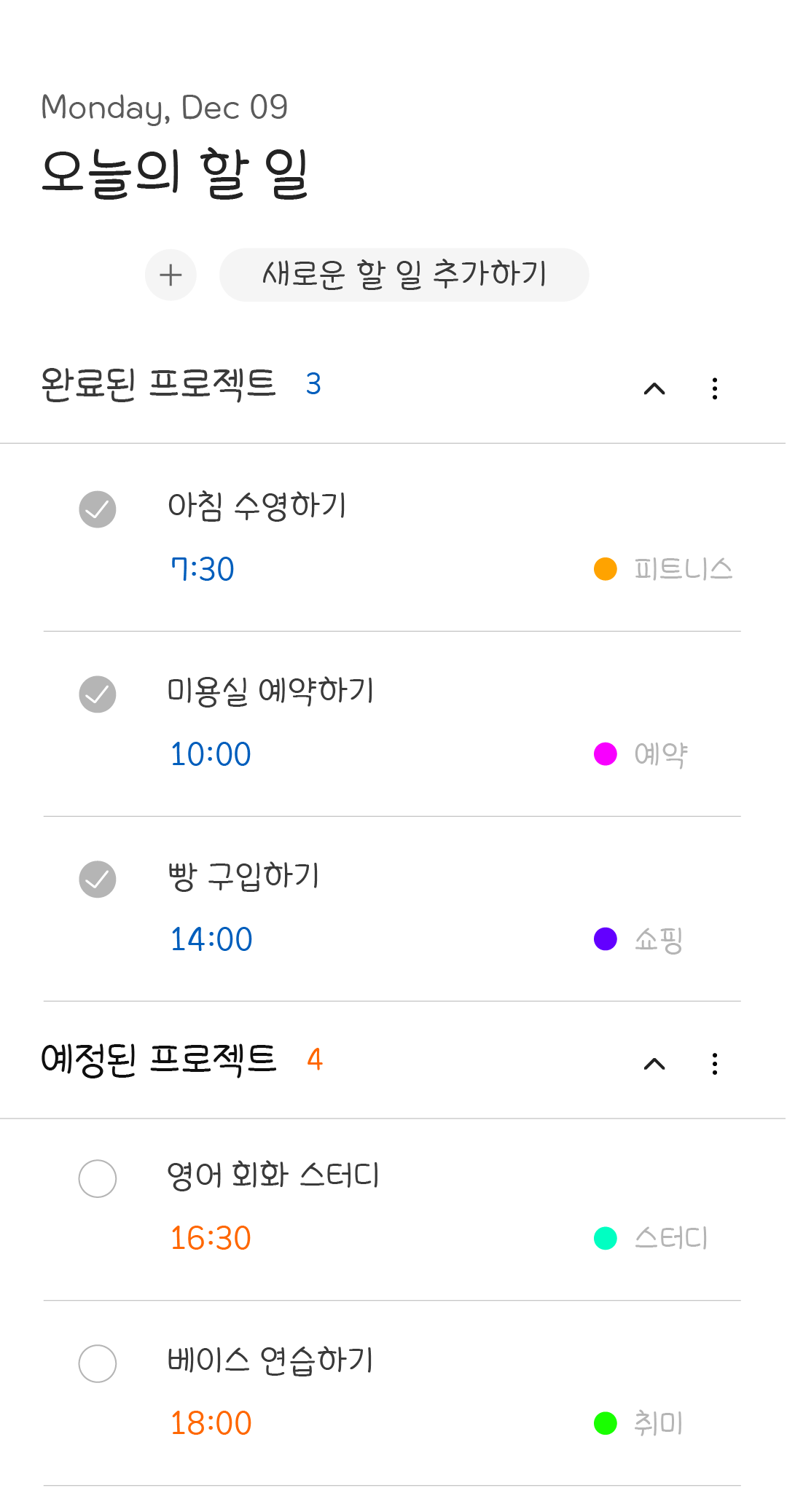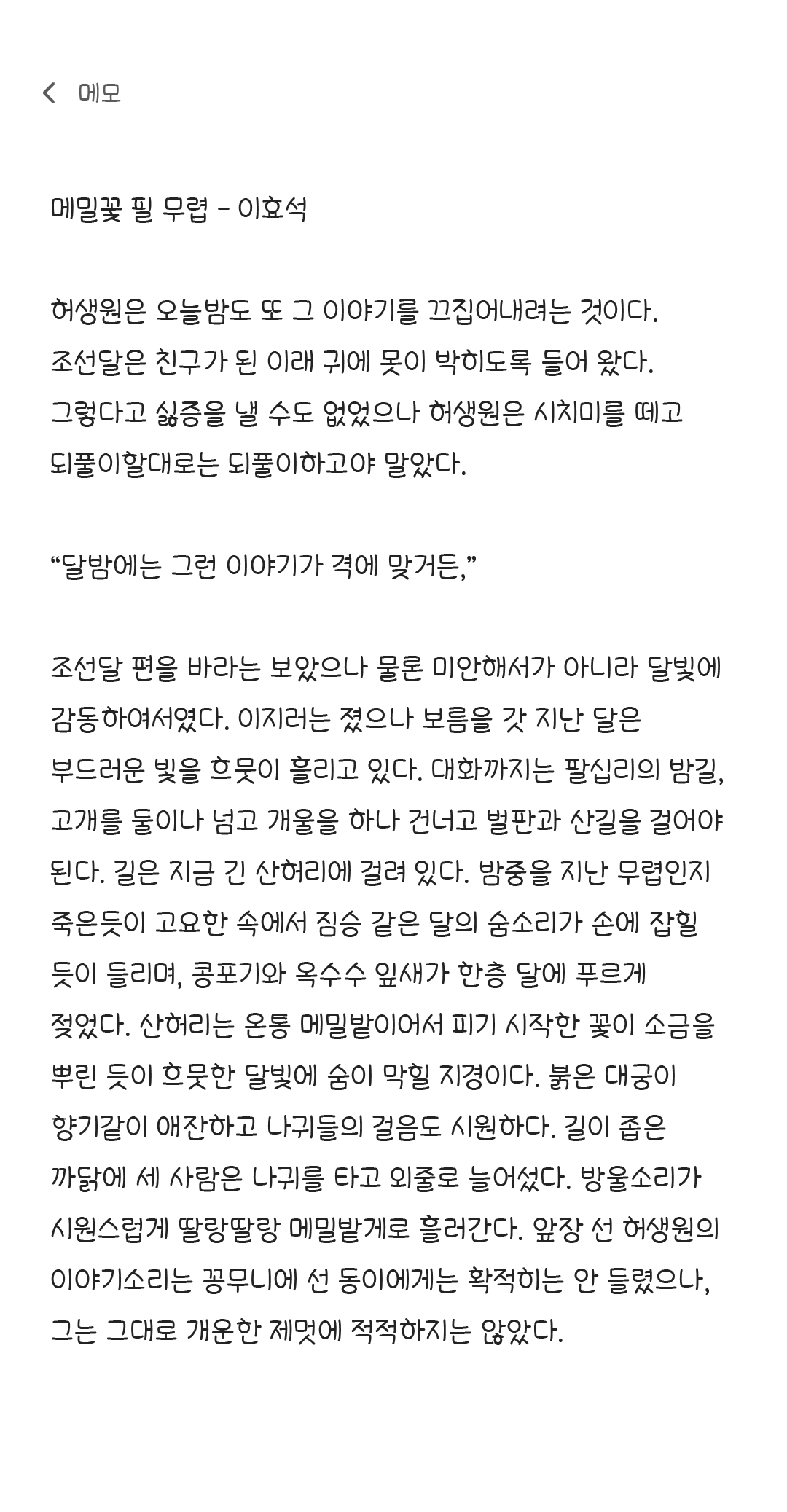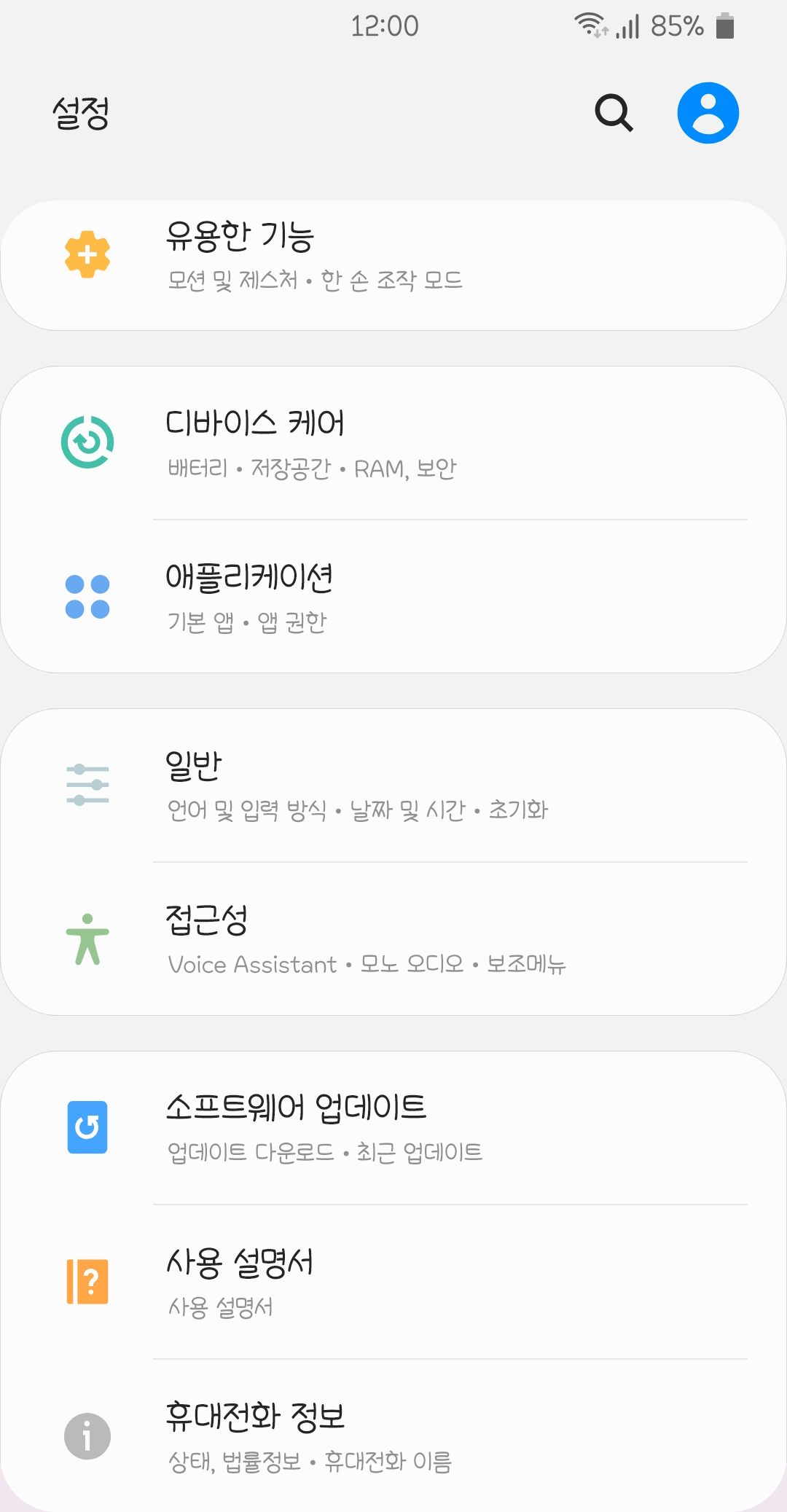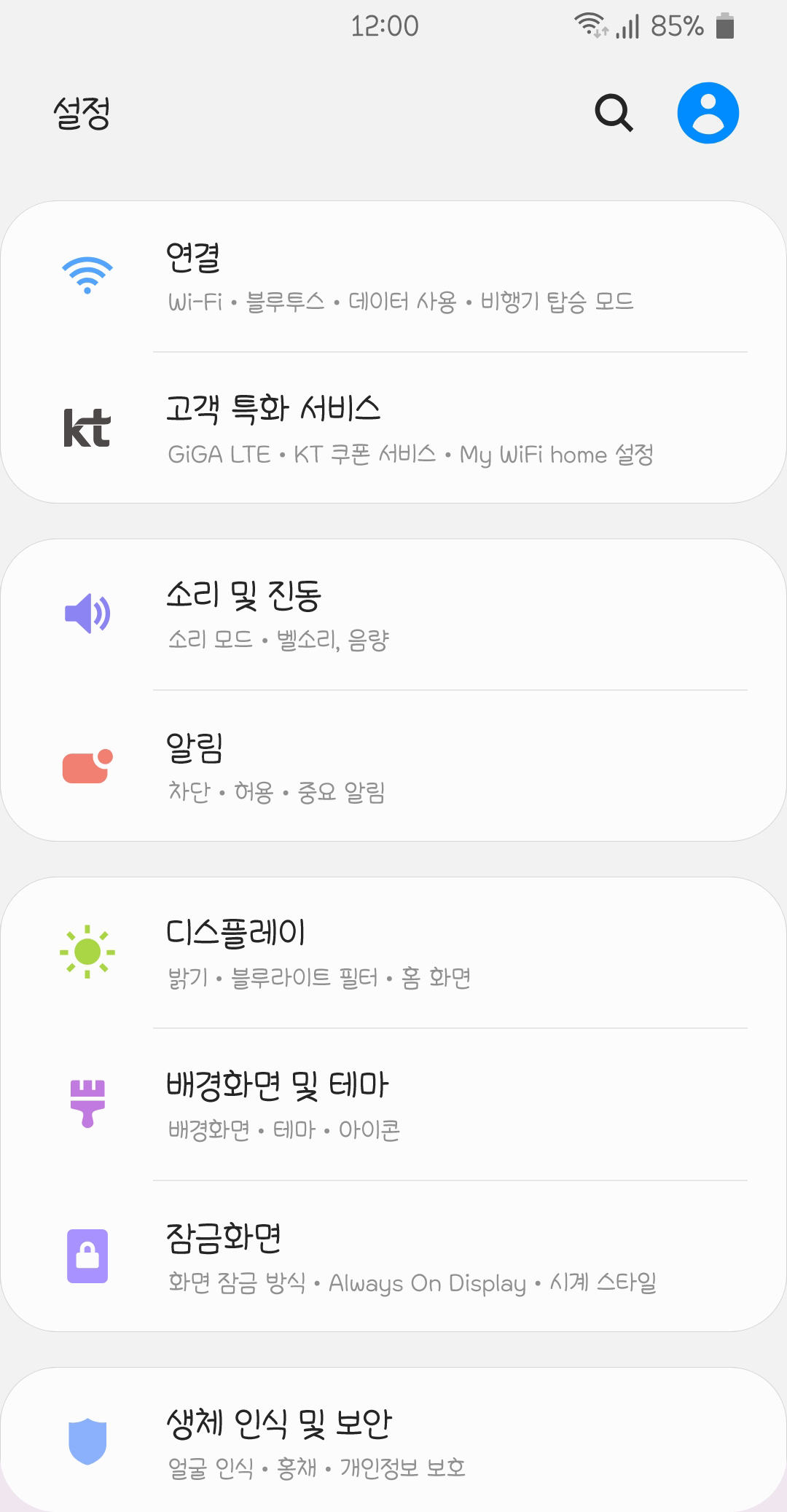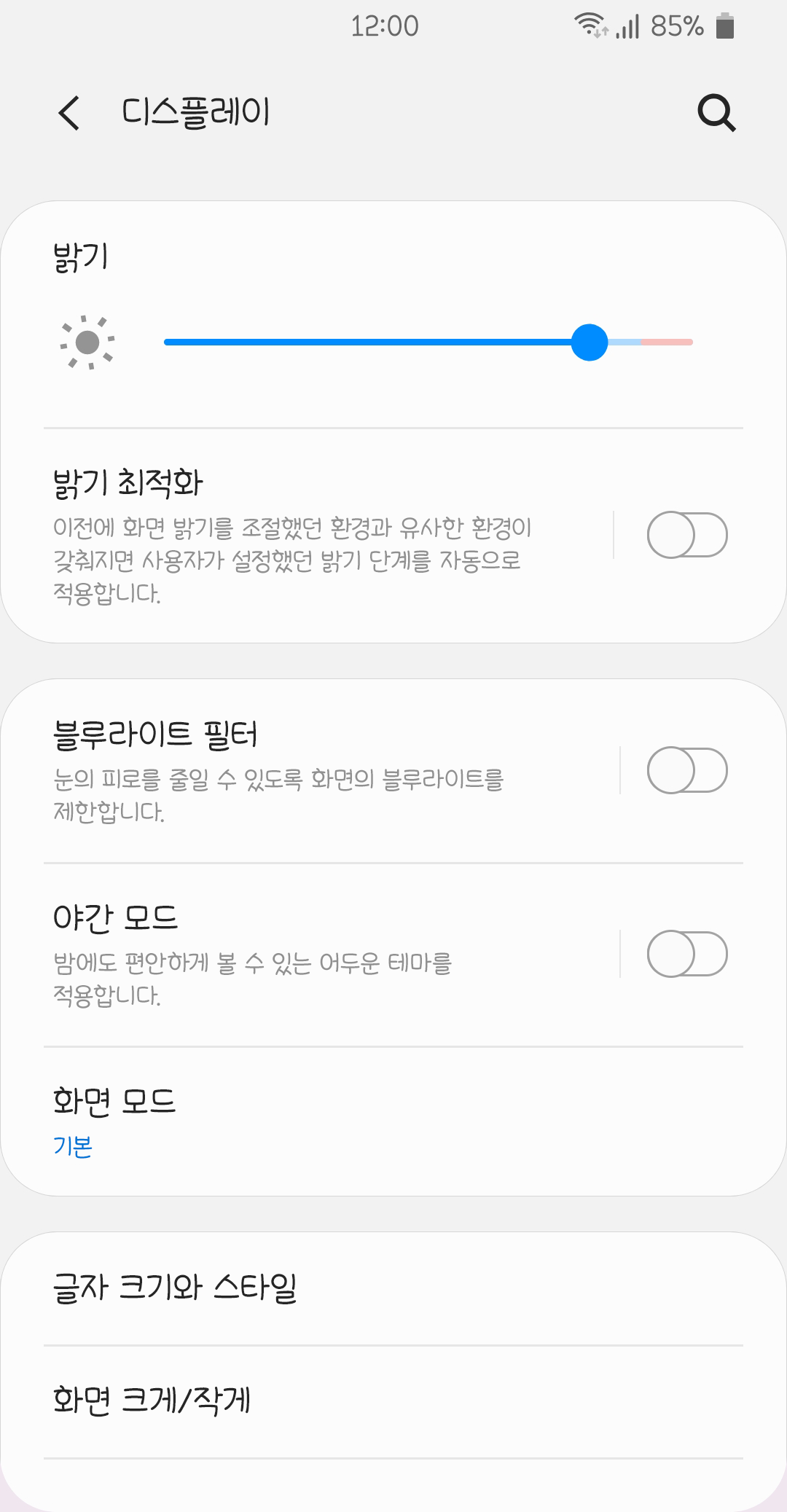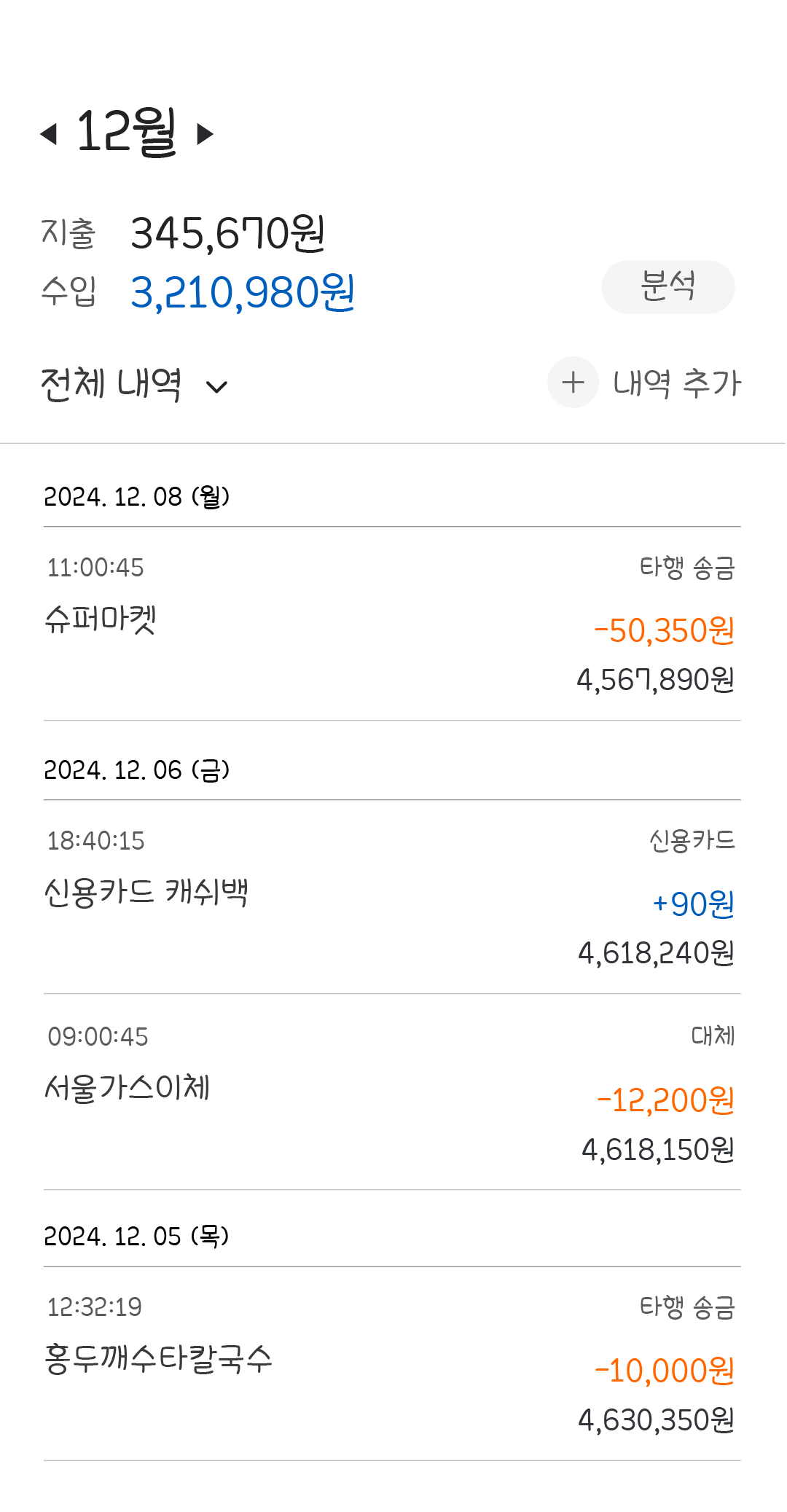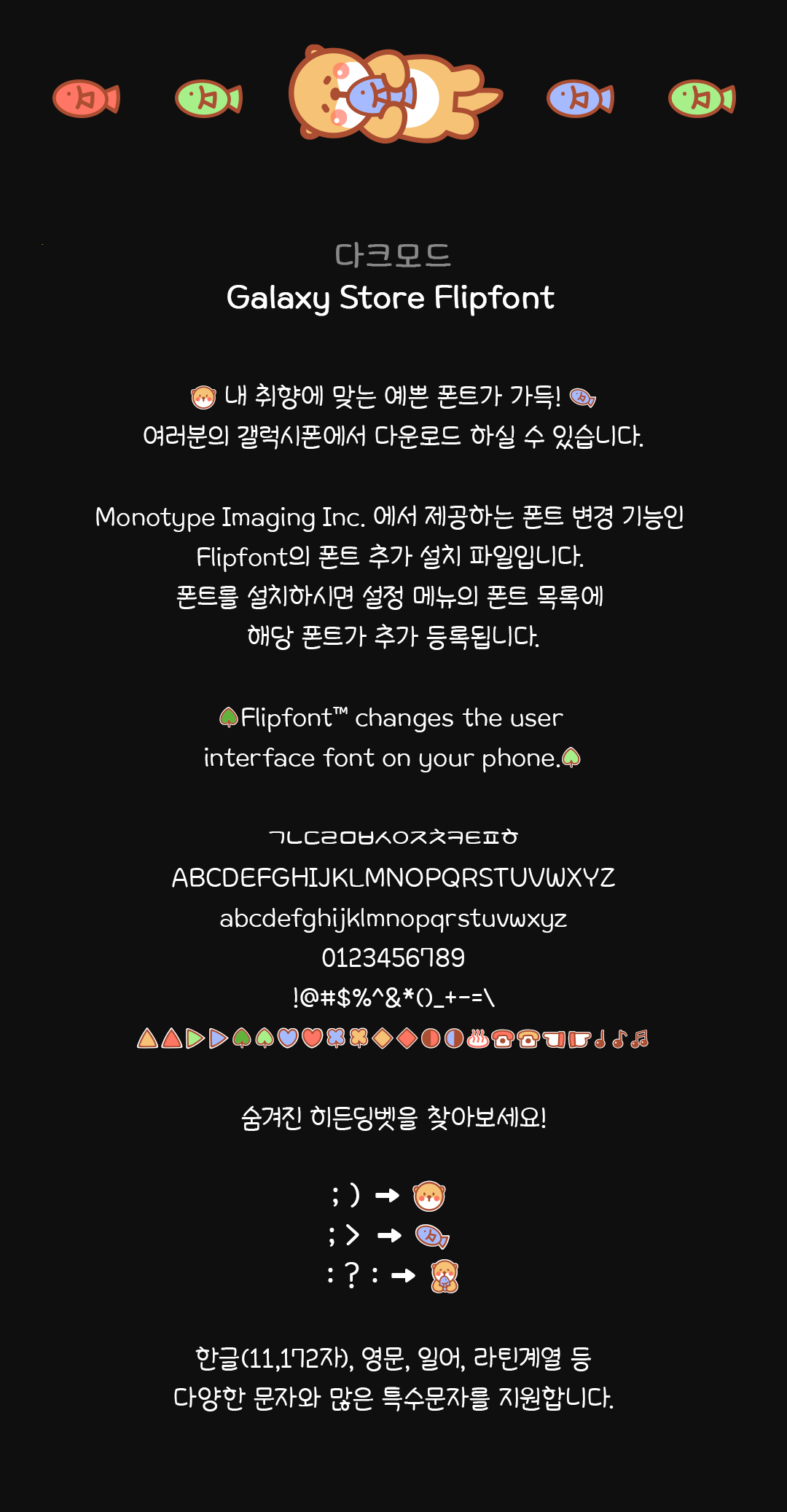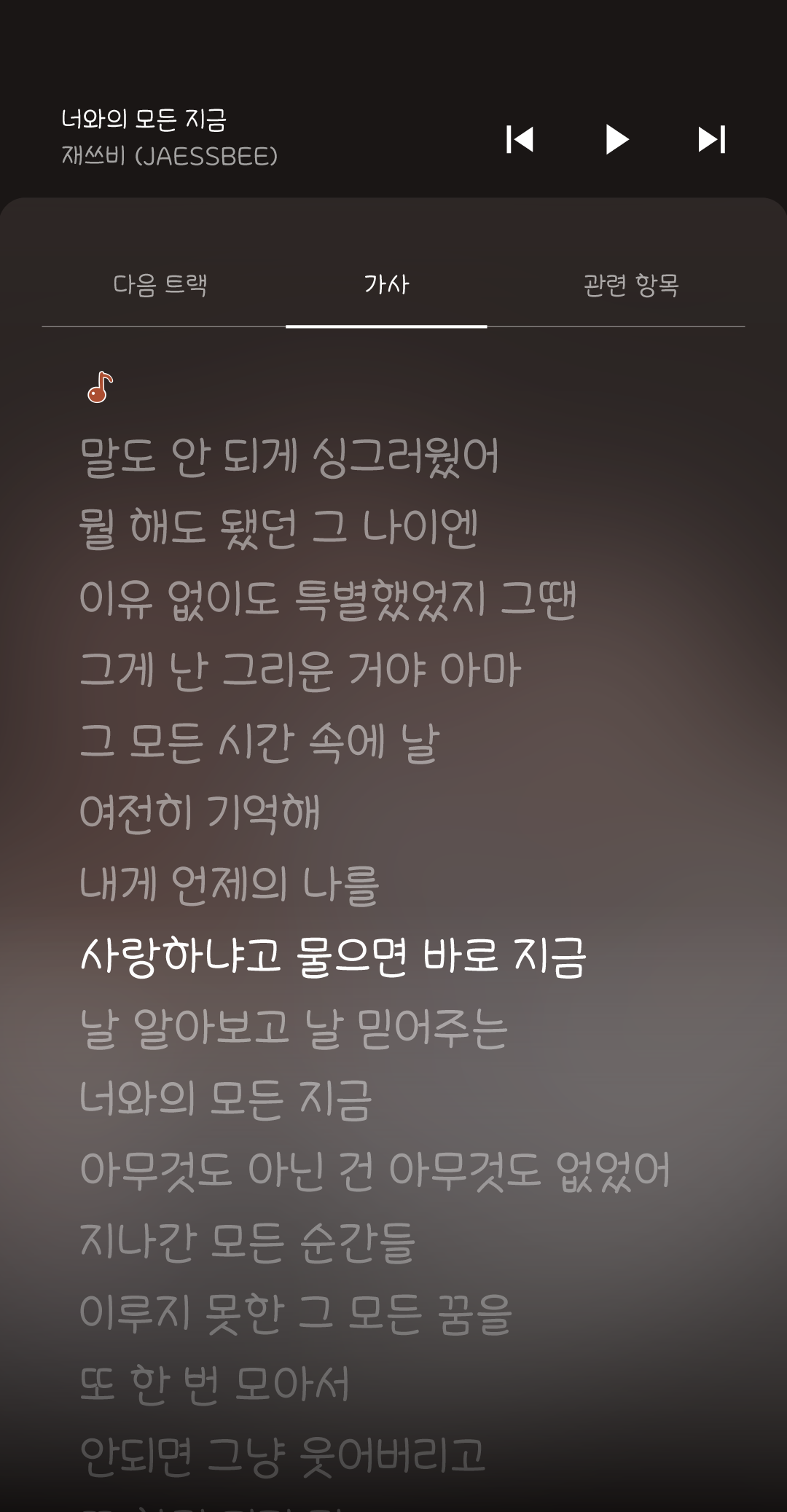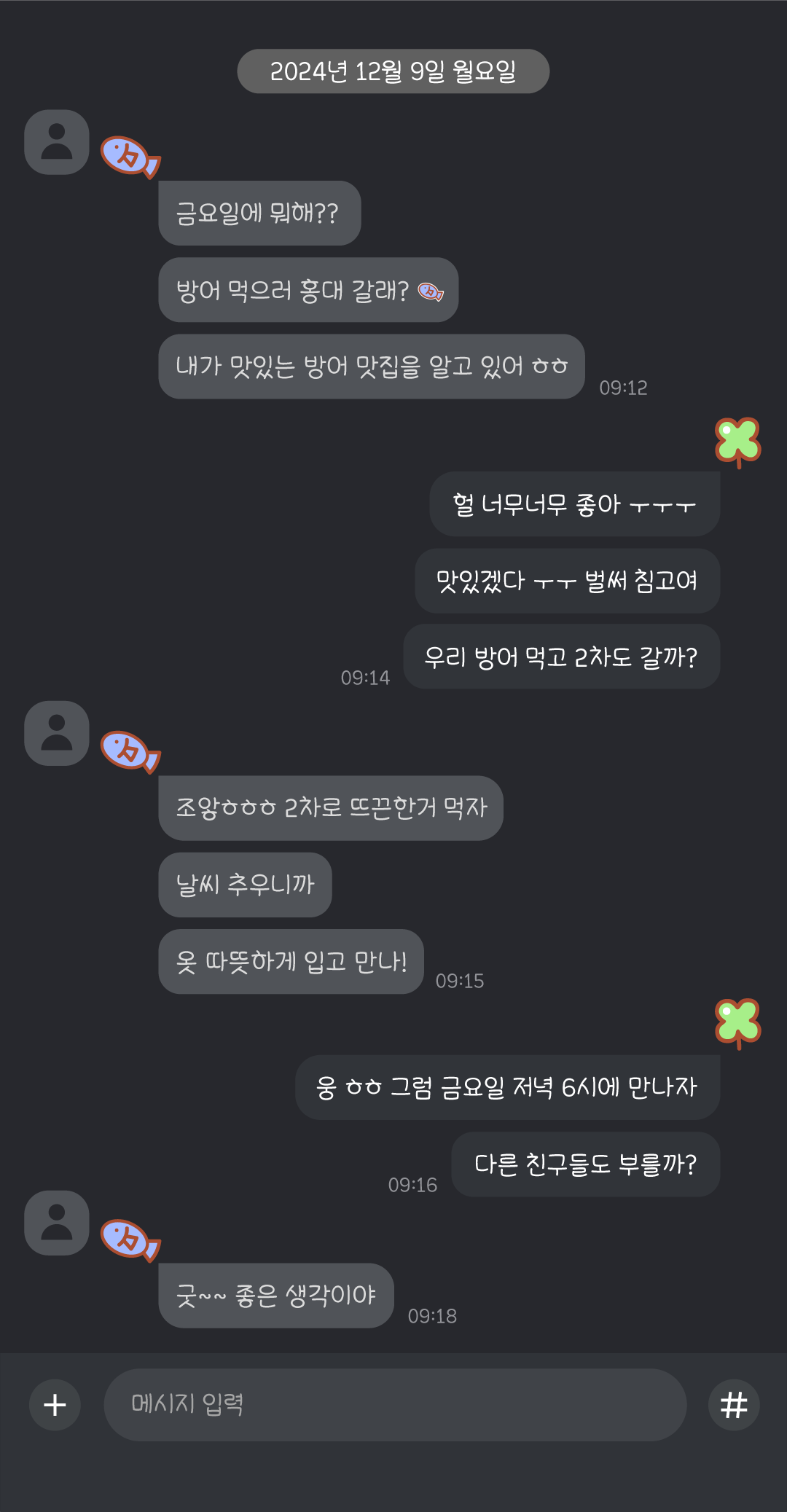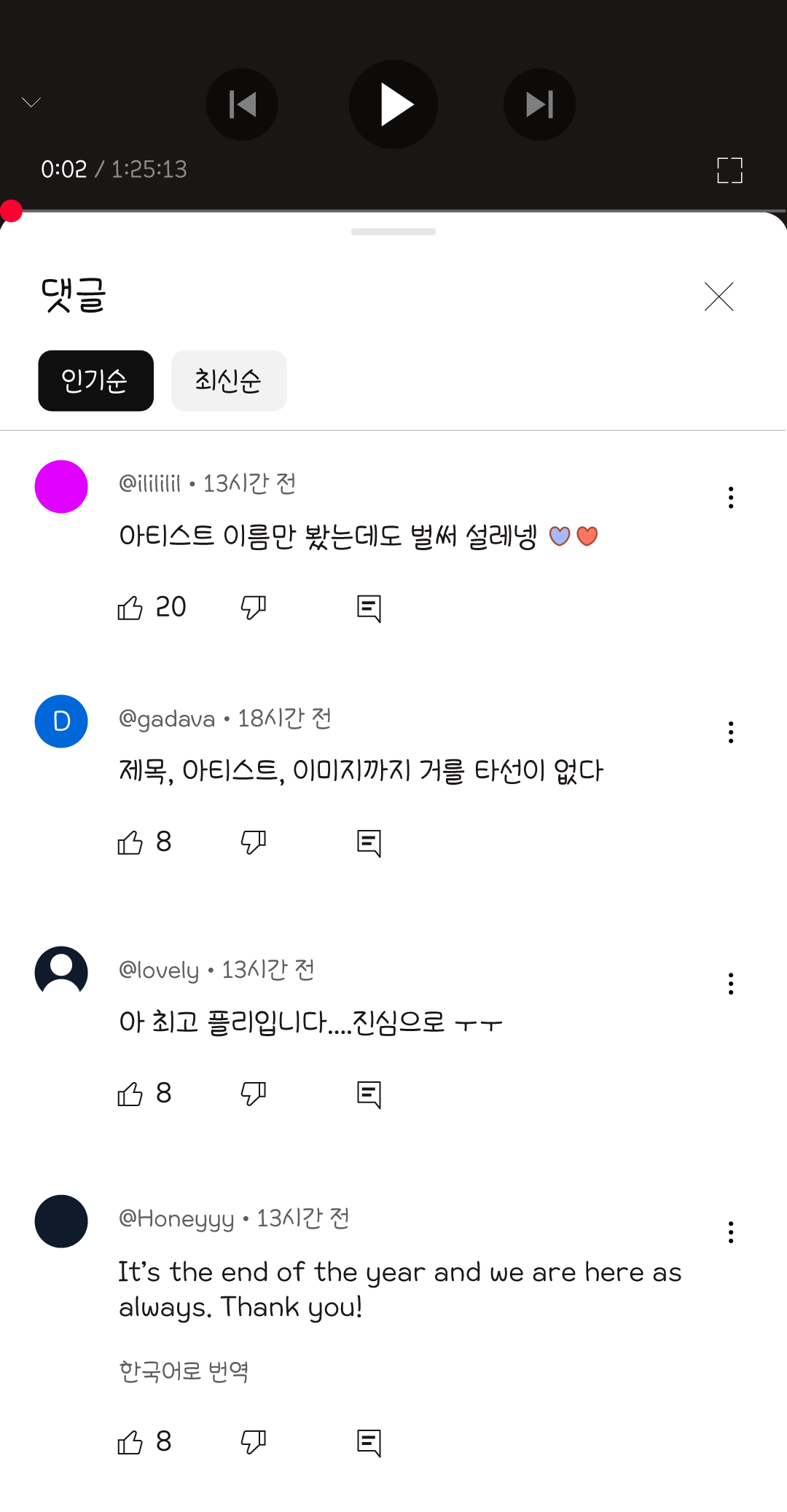
이 서체는 수달의 이미지처럼 귀엽고 둥근 인상이 특징입니다. 단정하고 부드러운 곡선의 손글씨 느낌을 살리고 동글동글한 획과 꽉 차고 큰 자소들이 귀여운 매력을 보여줍니다.
이 서체는 수달의 이미지처럼 귀엽고 둥근 인상이 특징입니다.
단정하고 부드러운 곡선의 손글씨 느낌을 살리고 동글동글한 획과
꽉차고 큰 자소들이 귀여운 매력을 보여줍니다.
TE 동그라미수달